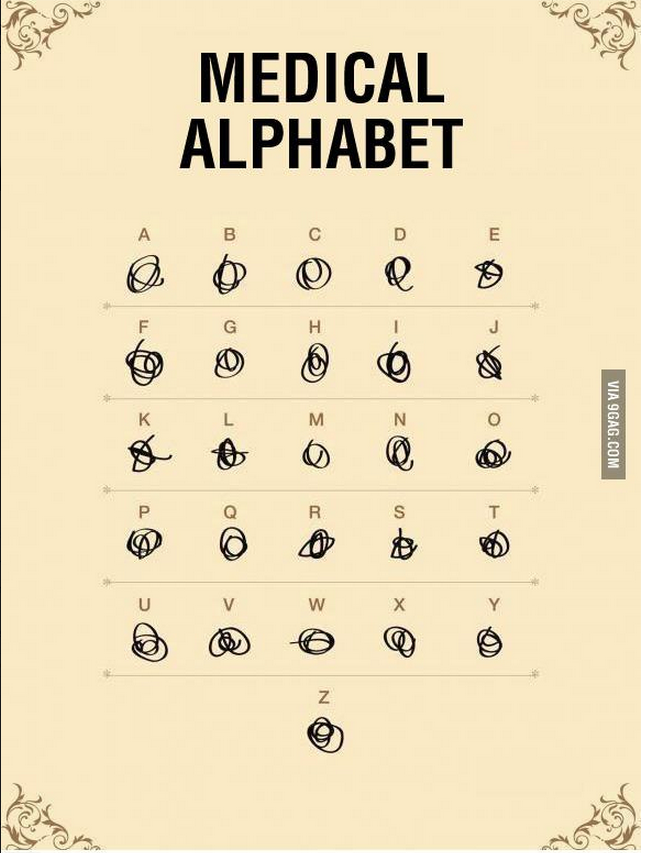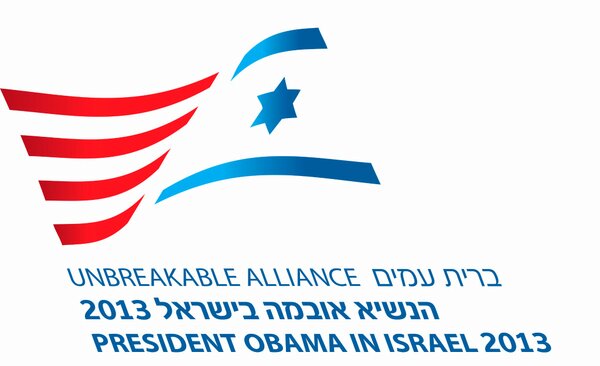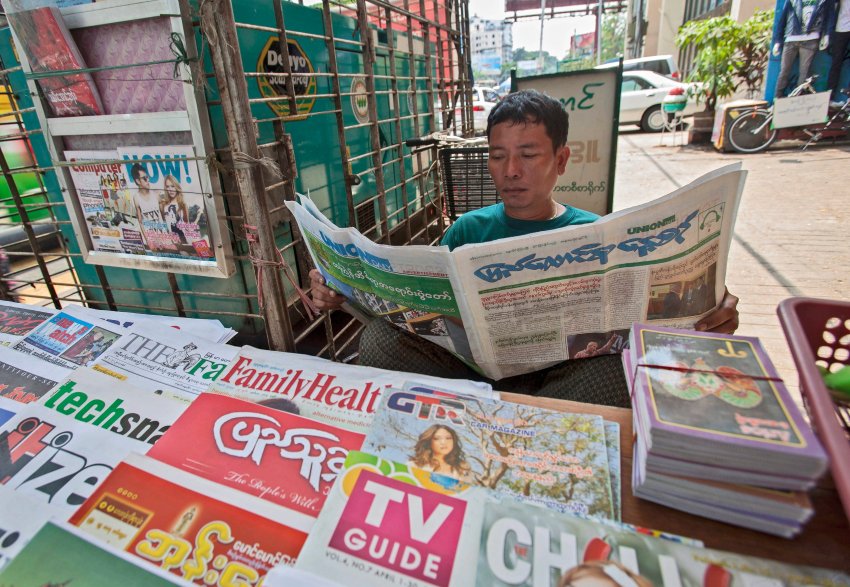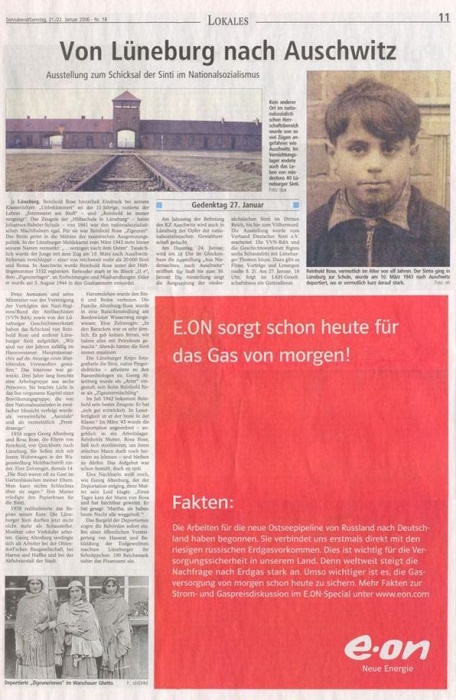
Doch. In der Vergrößerung kann man sogar nachvollziehen, daß dort nicht TROTZKI, sondern TROTZKY steht.
Na dann ... Ich hätte auf die Gebrauchsanleitung des Mac getippt ... ;-)
Neulich hatten wir ja das Thema Kursive in Verbindung mit Hebräisch. Das meint das Büro des israelisches Premiers dazu:
Logo, es ist ein Logo und damit nicht unbedingt aussagekräftig, was Mengentext angeht. Vielleicht soll die Linksneigung auch einfach nur die typische Orientierung einer »dynamisch flatternden« Flagge aufnehmen. :-?
Es gab übrigens mehrere Entwürfe.
Auf deutsch heißt es birmanisch, wenn es um Birma bzw. Myanmar geht. Andererseits: die Zeitschriften in englischer Sprache könnten ja aus Burma kommen, mit dem Eigenschaftswort burmese.
Bravo, Herr Oberlehrer! Ich hatte mir einfach mal erlaubt, mich nicht an die Vorschriften des Auswärtigen Amts zu halten, sonder daran, was ich für umgangssprachlich verständlicher halte.
Birmanisch, auch Burmesisch […]
Bei mathptmx werden bei mir einzelne Buchstaben im Pdf-Dokument verschmolzen oder berühren sich:
bei "fi" vershwindet der Punkt vom i komplett im Bogen vom f; und bei "ri", "rr", "rt" "Th" berühren sich die Buchstaben.
Gibt es ein schöneres Font, aber auch mit Times New Roman?
Das ist Absicht und kein Fehler. Es nennt sich Ligaturen und ist im Allgemeinen (wenn sie was taugen) eins der Zeichen einer guten Schrift.
Das sieht doch total hälich aus :-( Wenn ich verbundene Buchstaben haben will, nehm ich mir ne Schreibschrift.
Bei Word ist wenigstens noch der Punkt vom "i" zu sehen.
Ich bin nicht ganz sicher, aber ich vermute, dass der User nach einem anderen Paket such, dass die Times auch bereitstellt. In LaTeX werden Schriften in der Regel durch Pakete (zusätzliche Module/Extensions) bereitgestellt bzw. geladen und da gibt es tatsächlich mehrere, die verschiedene Versionen der Times laden … nur das alle diese hässlichen Ligaturen haben. Womöglich kommt als nächstes jemand auf die Idee echte Kapitälchen zu verwenden – das wäre schlimm